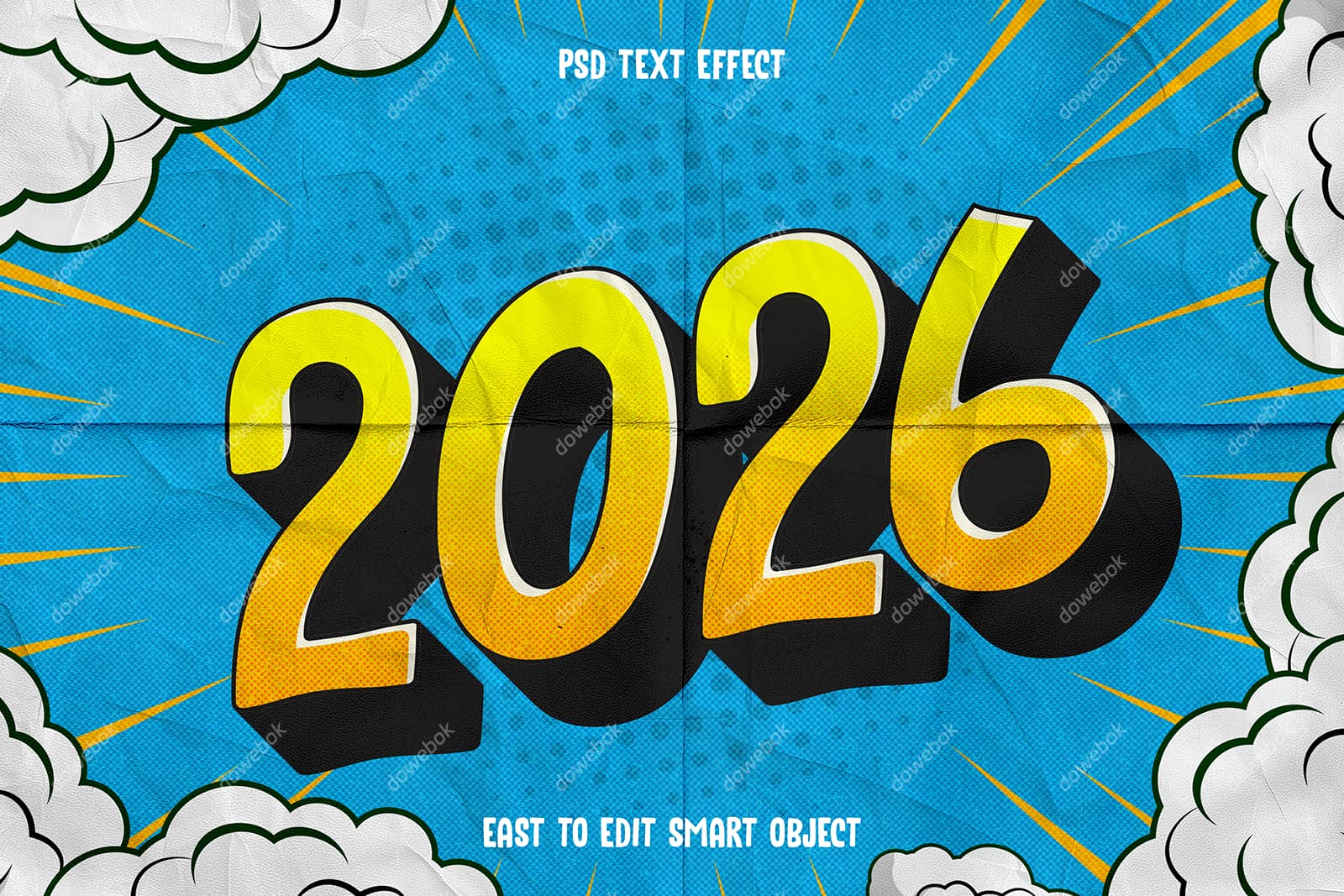
这是一款由漫画风格设计的 2026 新年快乐 PSD 素材,亮蓝褶皱背景配黄射线、卡通云装饰,“2026” 以黄黑渐变立体字呈现,边缘醒目且具漫画张力。顶部标 “PSD TEXT EFFECT”,底部注其为可编辑素材。整体风格活泼跳脱,撞色与波普元素结合,既显潮流创意,又点明字体效果的可编辑属性,适配年轻向创意海报等场景。